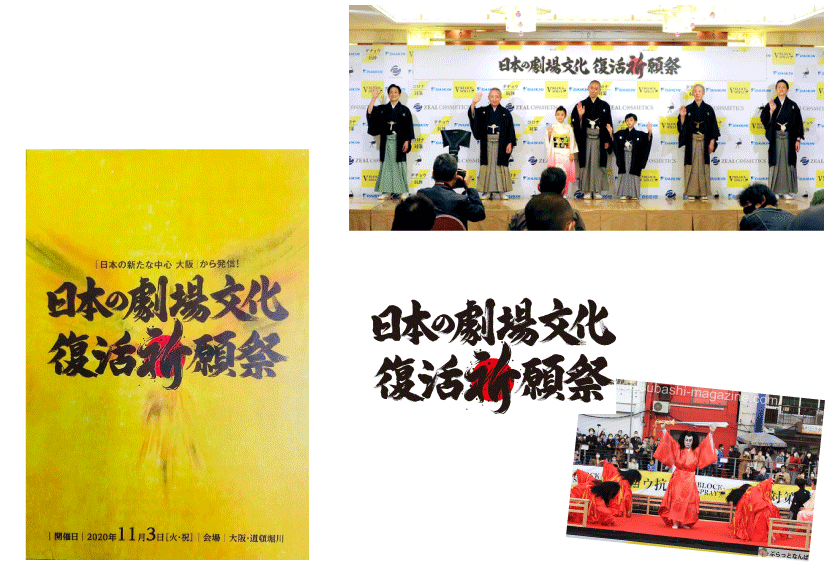
「復活祈願祭」題字
2020年11月、
打撃を受けた経済を一刻も早く取り戻したい一心で
歌舞伎俳優の市川海老蔵氏らが道頓堀から発信しました。
「天空狂言」壁面ポスター作成
4000mm×2500mm / 2000mm×2000mm
2001年から5年間、正月三ヶ日にOAPタワーにて催された「天空狂言」の為に描かせていただきました。
日本の豊かな祭り文化にあって伝統芸能は世界に通用する素晴らしい演舞です。
狂言を、絵、書き文字などによって、親しみやすくお客様と共に感じていただくのが、このポスターの役目とも言えます。
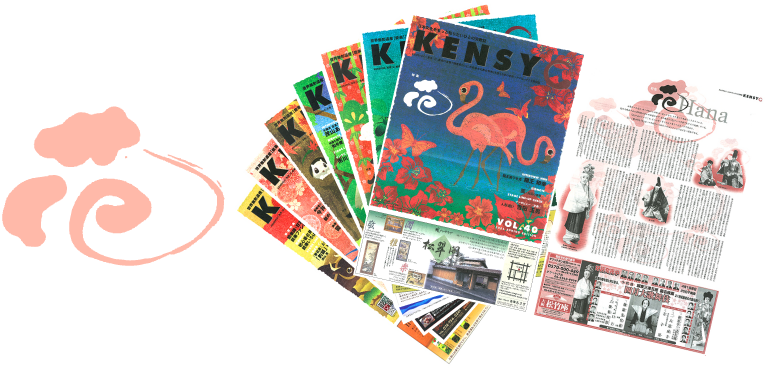
伝統芸能情報誌 「KENSYO」題字制作
1991年創刊 年4回発行
創刊から22年、世界無形遺産の情報誌として発刊し続け、毎回の特集にワビ、サビの世界観を包含する一文字を演出。
綿密な打合せと、裏付から描き続け現在に至る。
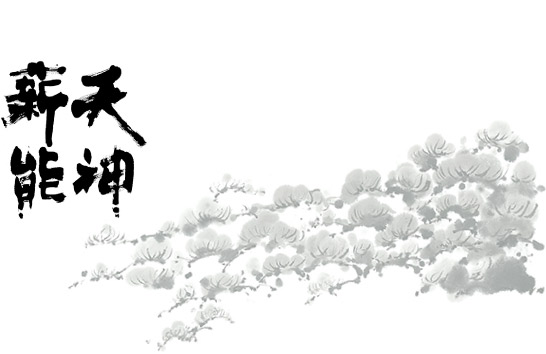
天神薪能チラシ題字
1996〜2001年
空中庭園の真下、開放的な空間でくり広げる新梅田シティー、
”天神薪能”は薪にゆらめく幻想的な能舞台を想像させるビジュアルに展開し、多くの観劇ファンを集めました。
茂山狂言公式本「和らい袋」
タイトル文字制作
発行:茂山狂言会 2000年、2009年発行
代々伝えられてきた伝統を守りながら、茂山家という大きな袋の中で喜んでもらえる狂言を提供し続ける一門。
まさに”和らい袋”なのです。その懐の深い手作り感こそに指文字として、思いをはせるのです。
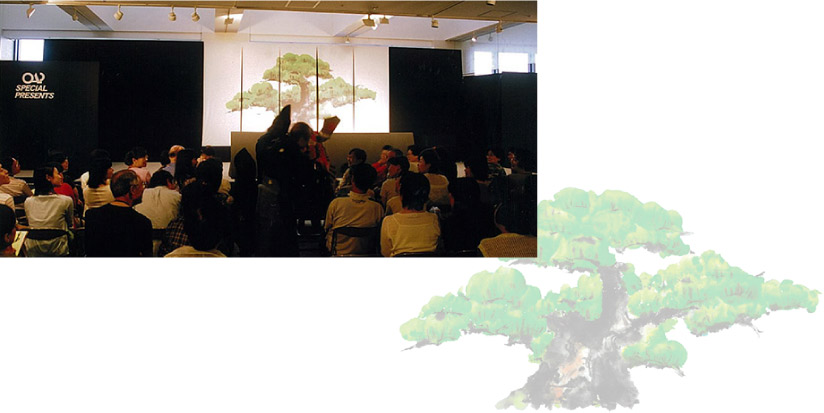
老松
能舞台の後部にある大きく描かれた老松は羽目板といろ鏡板のことです。本来舞台の正面、つまり観客のいる場所にその松があり、その松が鏡に映ったところを模したものとされています。その板を布に変えて演出してみました。